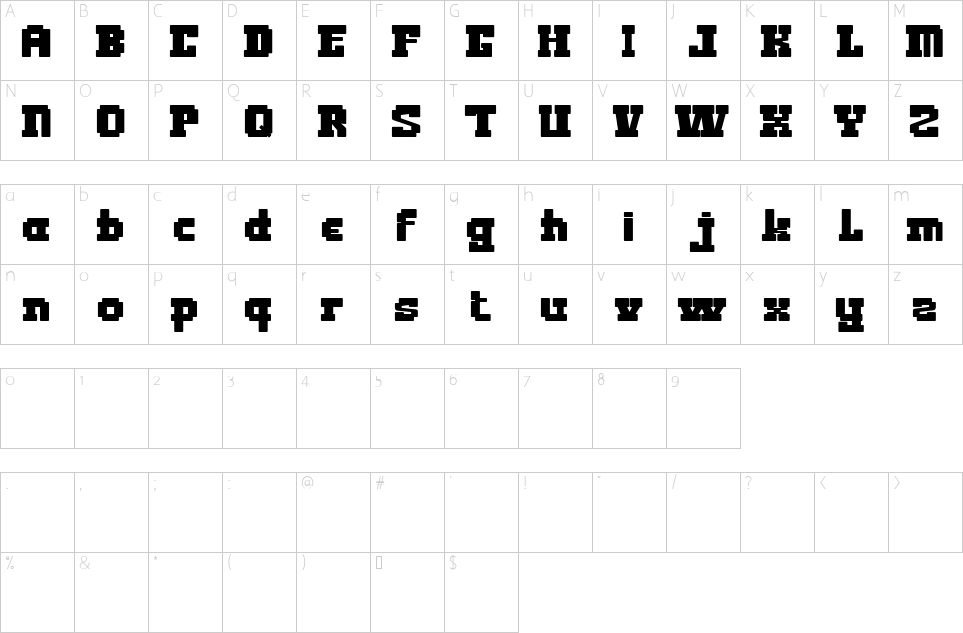
A Pixeland é uma fonte grata e única, desenhada pela Flawless And Co. Ela é uma escolha perfeita para designers que valorizam estilo e simplicidade. Sua forma geométrica e linhas retas criam um visual moderno e moderno que combina perfeitamente com diversas aplicações, seja em logos, websites ou até mesmo em designs de ilustração. Com uma linguagem de caracteres bem definida e uma ampla gama de opções de tamanho, a Pixeland é uma excelente opção para quem busca um estilo minimalista e sofisticado. Se você está procurando por uma fonte que combine perfeitamente com a sua visão de design, Pixeland é uma fonte que merece atenção.